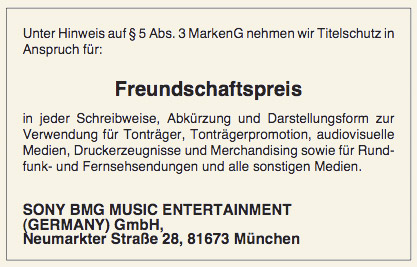
Billiges Apfel-LogoHallo Designer bei Sony BMG: Was »billig« verkaufen soll muss
nicht billig gemacht sein. Euer Freundschaftspreis-Apfel ist uninspiriert und
langweilig. Nehmt Ihr Eure Zielgruppe nicht ernst? Die Fans von Udo Jürgens
und Karl Moik? Das solltet ihr aber! Weiterlesen ...
![]() Sonst wandern die zu einem anderen Apfel ab, dem abgebissenen. Da ist die
Musik ebenfalls preiswert. Doch wie man den Medien jüngst entnehmen konnte,
wollt ihr das auch bald abstellen.
Im April ließ Sony BMG den Begriff Freundschaftspreis schützen: ![]() Dies geschieht ganz profan und ohne visuelles Brimborium im Titelschutzanzeiger. Jetzt kommt der optische Zuckerguss zum Namen, besser ein optischer Langeweiler: ![]() Unter dem Motto Freundschaftspreis will Sony BMG ab Mitte Oktober eine neue Marke im Mid-Price-Segment etablieren. Zum Kampagnenstart zeichnet das Unternehmen rund 60 CD- und DVD-Titel neu herunter, 450 Titel aus dem Backkatalog runden das Angebot ab. Die Marke Freundschaftspreis soll vor allem den Bereich Schlager und Volksmusik abdecken und somit für zumeist nationale Produktionen als Gegenstück zum bekannten Nice-Price-Segment fungieren. Sony BMG will den Freundschaftspreis mit einer Print- und PoS-Kampagne mit Deckenhängern sowie Boden- und Thekendisplays mit einem Mediawert in Höhe von rund 500.000 Euro am Markt etablieren. Gefunden bei musikwoche.de und nicorola.de Herausgegeben: Do - September 22, 2005 at 05:36 nachm. | |